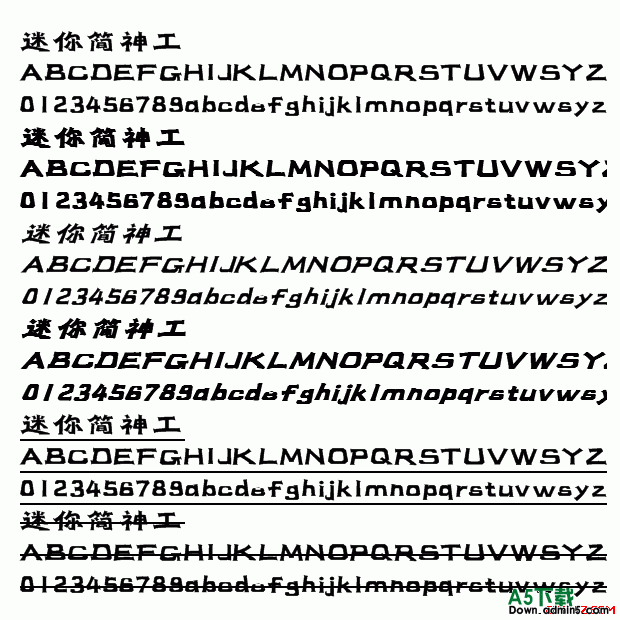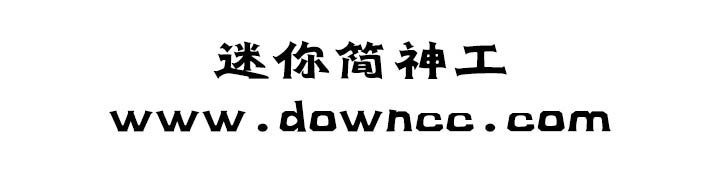
迷你簡(jiǎn)神工是一款應(yīng)用于廣告設(shè)計(jì)方面的中文簡(jiǎn)體漢字,字形大方端正,但不是很工整,可以應(yīng)用于兒童繪畫,藝術(shù)設(shè)計(jì),廣告平面設(shè)計(jì)、包裝印刷等領(lǐng)域,有喜歡的用戶可到綠色資源網(wǎng)下載收藏。
4、迷你簡(jiǎn)神工字體設(shè)計(jì)的字體有沒,自形清晰,對(duì)于封面的文字編輯是非常美觀的